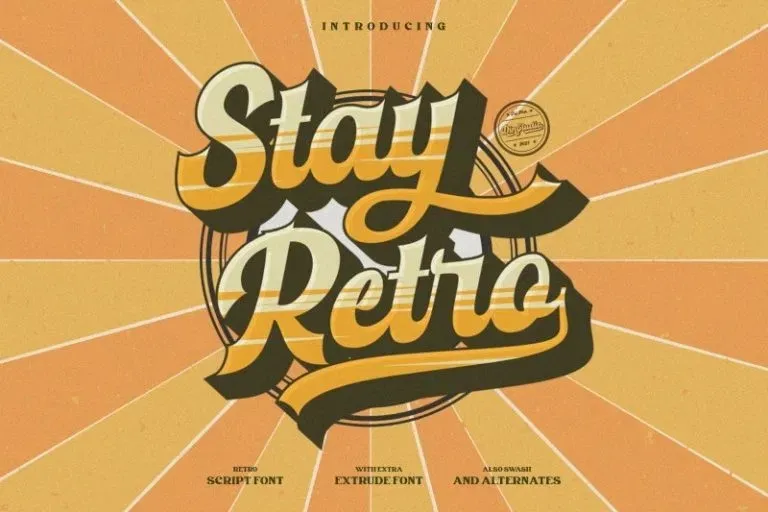
Stay Retro Font
Esta fonte script é uma clássica que incorpora as curvas elegantes do estilo retro. Ela adiciona saltos estilizados e ligaturas para tornar esta fonte ainda mais única, destacando-a entre outros typographies. Este tipo de letra bubblescript é perfeito para um número ilimitado de necessidades de conteúdo e projetos. É uma escolha excelente para adicionar o certo toque de atmosfera urbana e leveza. Você pode usá-la para criar citações bonitas, embalagens chamativas ou belas camisetas! E você também pode usá-la para criar incríveis cabeçalhos, logotipos, menus e gráficos para mídias sociais! Estamos certamente ansiosos para que o público seja capaz de experimentar a magia deste design, tanto no conforto da sua casa quanto em eventos mais formais. Estas fontes script têm uma personalidade rica, capaz de dar um toque especial às coisas mais simples e aos projetos mais elaborados. Afinal, quando você tem o poder de transformar qualquer tipo de material digital ou impresso em algo único e memorável, a criatividade é apenas limitada pela sua imaginação.